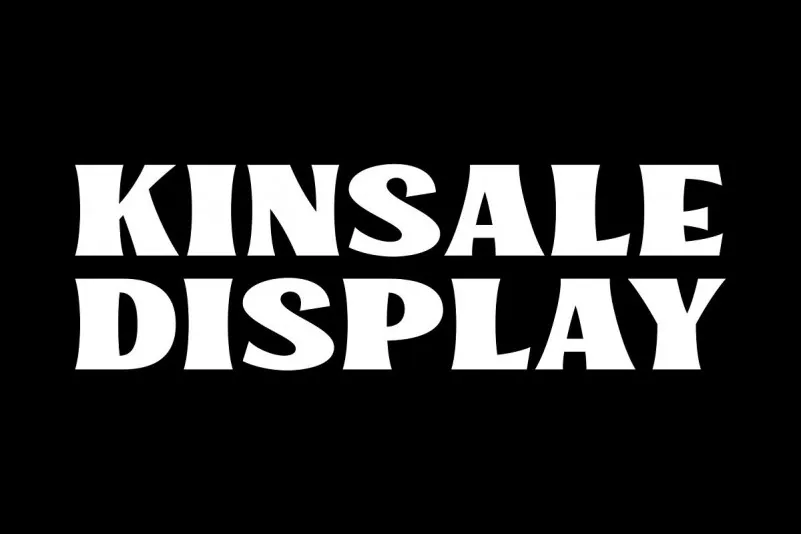
Kinsale Display Font
Esta página de download apresenta a Kinsale Display Font, uma elegante serifless com traços modernizados, criada pelo designer C00zona. A Kinsale Display é um tipo forte e robusto, que se inspira na estética vintage mas também incorpora sutis toques modernos e absurdos. Este design de fonte de exibição foi projetado para ser versátil e combinável com várias outras fontes, tornando-se um excelente complemento para qualquer projeto. As linhas finas e aguçadas e as curvas atraentes da Kinsale garantem uma aparência limpa e moderna. Seus letras largas e retangular fornecem espaço suficiente para ser usado como um “spacekiller”, ideal para títulos, headlines, logotipos, embalagens ou rótulos de produtos. A atenção meticulosa ao detalhe da fonte garante uma estética profissional que combina a simplicidade moderna com o charme vintage dos traços tradicionais.